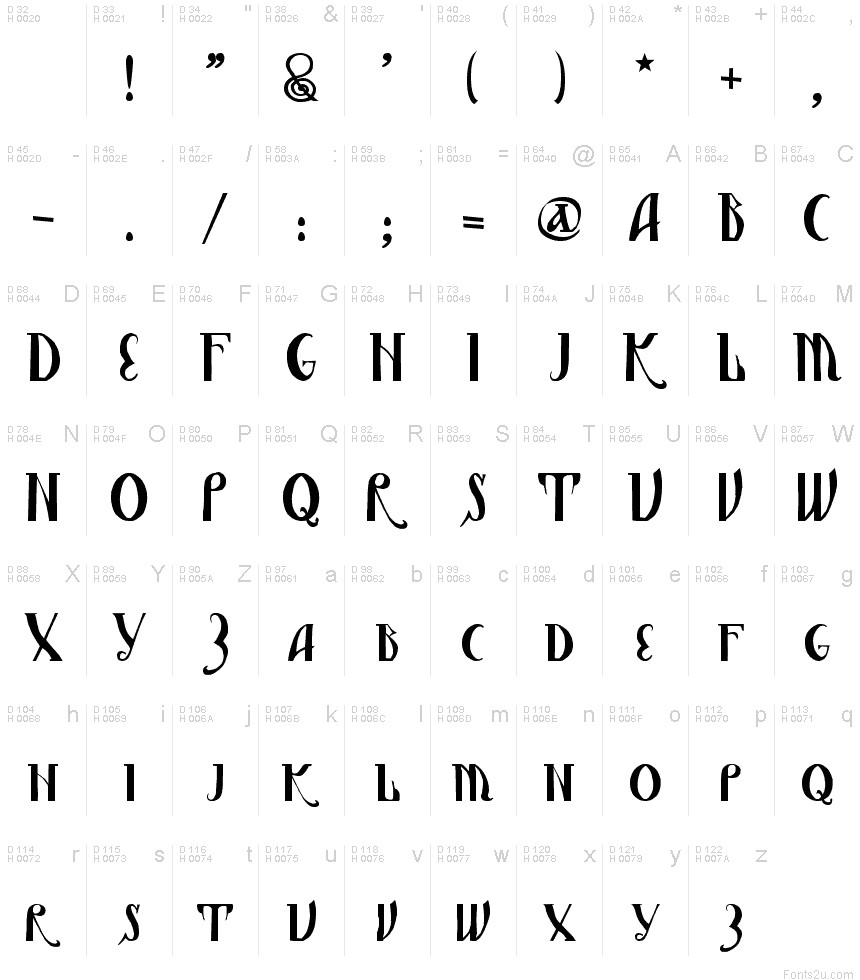
Vasilisa Demo autorstwa Davida F. Nalle’a to darmowy krój retro typu display z wysokimi, ostro ciętymi literami i wyraźnie odręczną sylwetką. Wyraziste kontrasty grubości kresek, zaostrzone końcówki i nierówne kontury przywodzą na myśl liternictwo teatralne, a nie tradycyjny krój szeryfowy.
Wydawnictwo fantasy lub butik z kostiumami mogą wykorzystać go w identyfikacji wizualnej, na okładkach książek, opakowaniach i drukowanych plakatach okolicznościowych. Najlepiej sprawdza się w dramatycznych nagłówkach z nutą mrocznej baśni.